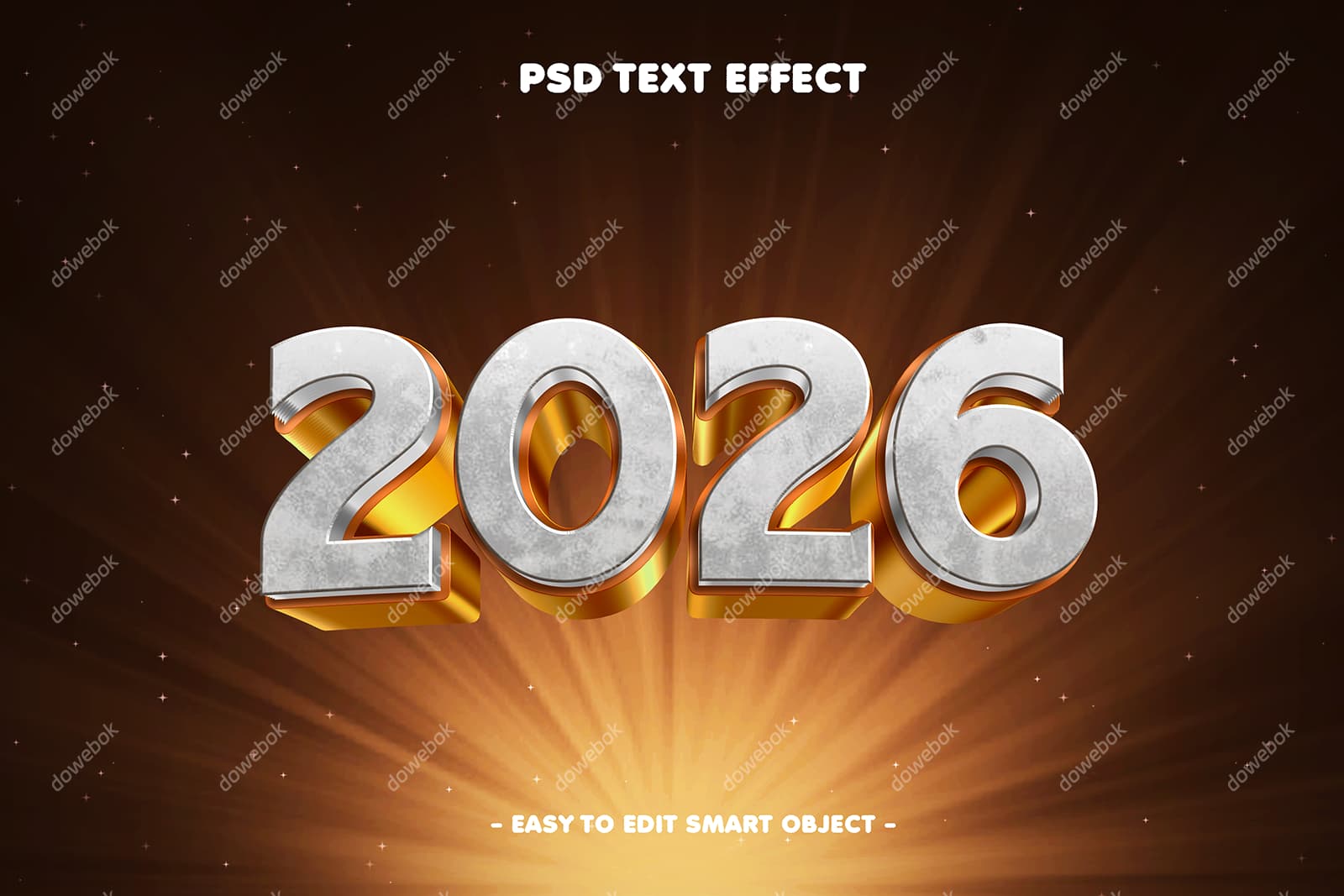
这是一款由金属立体数字设计的 2026 新年快乐 PSD 素材,深棕背景衬着暖金放射光与星光,“2026” 以银灰金属质感立体字呈现,边缘镶金,质感硬朗精致。顶部标注 “PSD TEXT EFFECT”,底部说明其为可编辑素材。整体银金配色兼具工业风与高级感,既突出字体效果的质感,也点明其可编辑属性,适配工业风、科技风创意物料等场景。